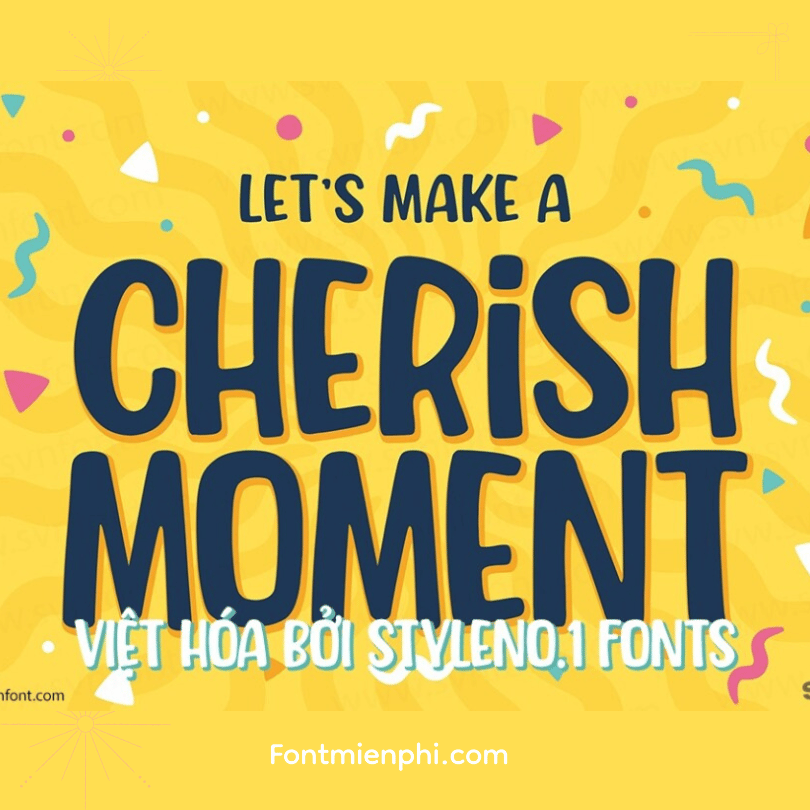
Việt hóa font SVN Cherish Moment
Việt hóa font SVN Cherish Moment – Nét Chữ Thanh Lịch, Lãng Mạn
Font SVN Cherish Moment đã được Việt hóa hoàn chỉnh, mang phong cách chữ kịch bản (script) mềm mại với những nét lượn sóng duyên dáng. Font hoàn hảo cho thiết kế thiệp cưới, lời chúc, logo thương hiệu sang trọng hay các dự án cần sự lãng mạn, tinh tế.
Đặc điểm nổi bật:
✔ Hỗ trợ đầy đủ dấu tiếng Việt
✔ Nét chữ tự nhiên như viết tay
✔ Phù hợp in ấn và thiết kế digital